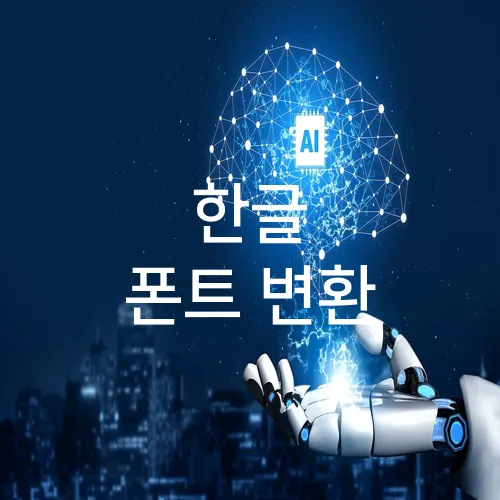
1. 한글 폰트 변환: 사용하기 쉬운 도구 및 애플리케이션
한글 폰트 변환을 위한 쉽고 유용한 도구
한글 폰트 변환은 많은 사람들이 다양한 목적을 위해 필요로 합니다. 이렇게 다양한 목적을 이루기 위해서는 사용하기 쉬운 도구와 애플리케이션이 중요합니다. 먼저, 대표적인 도구인 네이버 클라우드의 ‘네이버 폰트’는 100여 가지 이상의 다양한 폰트를 제공하여 사용자들이 손쉽게 자신만의 스타일을 완성할 수 있게 도와줍니다.
다음으로 추천할 만한 도구는 어도비의 ‘어도비 폰트’입니다. 이 도구는 웹 기반의 그래픽 작업 시 자동으로 폰트를 동기화하여 빠르고 효율적인 작업이 가능하도록 합니다. 특히, 어도비 스위트를 사용하는 디자이너들에게 최적화된 옵션입니다.
누구나 사용 가능한 무료 애플리케이션
무료로 제공되는 ‘구글 폰트’는 웹에서 바로 사용 가능한 오픈 소스 폰트 라이브러리로, 누구에게나 추천할 만한 서비스입니다. 다양한 글꼴을 웹 페이지에 적용하기 용이하며, 한글뿐만 아니라 다국어 폰트도 쉽게 변환할 수 있습니다.
또한, ‘다폰트 (Dafont)’는 사용하기 쉬운 사용자 인터페이스로 초보자도 손쉽게 필요한 폰트를 다운로드하여 사용할 수 있습니다. 특히, 상업적 이용 여부를 명확히 표시해줘 디자이너들이 안전하게 사용할 수 있습니다.
온라인 기반의 간편한 폰트 변환 기능
‘폰트 스퀘어’는 온라인에서 간단하게 폰트를 변경할 수 있는 서비스로, 별도의 프로그램 설치 없이 다양한 폰트를 테스트해볼 수 있습니다. 또한, 미리보기를 통해 지정된 텍스트가 실제로 어떻게 보일지 확인할 수 있습니다.
마지막으로, ‘윈도우 10’ 자체 기능으로도 기본 내장된 여러 한글 폰트를 쉽게 변경할 수 있으며 시스템 설정을 통해 간단히 적용이 가능합니다. 특히, 오피스 프로그램과의 호환성이 뛰어납니다.
이처럼 다양한 도구와 애플리케이션을 활용하면 한글 폰트 변환을 보다 쉽게 수행할 수 있습니다. 여러 옵션을 비교하고 자신의 니즈에 맞는 도구를 선택해보세요.
2. 웹사이트에서 한글 폰트 변환의 최신 트렌드
최신 웹사이트 트렌드
요즘 웹디자인에서 한글 폰트 변환이 어떻게 적용되고 있는지에 대한 트렌드를 살펴보겠습니다. 웹사이트는 단순히 정보를 전달하는 것을 넘어 감성을 표현하는 미디어로 자리잡고 있습니다. 특히 한글 폰트의 경우 시각적인 효과를 더욱 돋보이게 할 수 있어 많은 디자이너들이 주목하고 있습니다.
• 네이버와 카카오 같은 대형 포털 사이트는 최신 폰트 기술을 적극적으로 활용해 사용자의 가독성을 높이고 있습니다. 반응형 웹디자인과 같은 방식으로 다양한 기기에서 최적의 폰트 크기와 형태를 유지합니다.
• 웹폰트 서비스인 산돌클라우드와 같은 플랫폼은 사용자가 쉽게 웹사이트에 한글 폰트를 적용할 수 있는 환경을 제공하고 있습니다. 다양한 폰트 라이브러리를 통해 브랜딩에 맞는 폰트를 빠르게 적용할 수 있습니다.
디지털 환경에서의 한글 폰트 활용
디지털 디자인에서 한글 폰트 변환은 로딩 속도 최적화와 밀접하게 관련되어 있습니다. 최적화된 폰트는 웹페이지 로딩 시간을 줄이며, 이는 검색 엔진에서도 긍정적인 영향을 미칩니다.
• 구글 웹폰트와 이와 비슷한 서비스는 용량을 최소화한 폰트를 제공하여 페이지 로딩 속도를 개선합니다.
• 또한, 사용자 경험을 고려해 적절한 레이아웃과 폰트 크기를 적용함으로써 접근성을 높이는 것이 중요합니다.
변화하는 웹디자인 트렌드에 발맞춰 한글 폰트 변환 기술과 활용법을 이해하고 적용한다면, 더욱 매력적이고 효과적인 웹사이트를 구축할 수 있습니다. 이러한 트렌드는 사용자 만족도를 증대시키고 브랜드 이미지를 강화하는 데 큰 도움이 됩니다.
3. 한글 폰트 변환 시 주의해야 할 폰트 호환성 문제
한글 폰트 변환의 중요성
한글 폰트 변환을 할 때 가장 중요한 것은 호환성입니다. 이는 서로 다른 소프트웨어나 디지털 플랫폼 간에 문서를 공유할 때 발생할 수 있는 문제를 피하기 위해 필수적입니다. 최근 Adobe의 ‘한글본’이나 네이버의 ‘나눔글꼴’ 같은 무료 폰트는 높은 인기를 끌고 있지만, 여전히 폰트마다 호환성 이슈가 존재할 수 있습니다.
– 사용 중인 소프트웨어의 지원 폰트 리스트를 항상 확인하세요.
– 다양한 플랫폼에서 테스트하여 글꼴이 제대로 적용되었는지 확인하세요.
호환성 문제의 원인과 해결책
한글 폰트 변환 시 문제는 주로 문자 코드와 관련이 깊습니다. 특히 구형 소프트웨어와 신형 폰트를 사용할 때 이러한 문제가 자주 발생합니다. MS 워드와 같이 많은 사람들이 사용하는 프로그램에서도, 오래된 버전에서는 새롭게 출시된 한글 폰트가 깨질 수 있습니다.
– 최신 소프트웨어로 업그레이드하여 문제를 방지하세요.
– Google Docs 같은 클라우드 기반 서비스는 자동 변환 기능을 제공하여 호환성을 높입니다.
안정적인 폰트 변환을 위한 팁
변환 전, 항상 백업을 만들고 테스트 문서를 준비하는 것이 좋습니다. InDesign 같은 그래픽 소프트웨어는 복잡한 레이아웃에서도 폰트 호환성을 유지하는 데 유용합니다.
– Adobe Fonts를 이용하면 다양한 플러그인과 호환 가능합니다.
다양한 플랫폼에서의 테스트
모바일과 웹에서도, 한글 폰트는 각기 다른 해상도와 환경에서 다르게 보일 수 있습니다. 따라서 실제 사용 환경에서 폰트가 어떻게 보이는지 테스트하세요.
– iOS와 Android 모두에서 테스트하여 모바일 호환성을 높이세요.
– 웹사이트 구축 시, 다양한 브라우저에서의 시각적 차이를 점검하세요.
이러한 방법들을 통해 적절한 한글 폰트 변환을 거쳐, 프로젝트의 완성도를 높여보세요.
4. 창의적인 디자인을 위한 한글 폰트 커스터마이징 팁
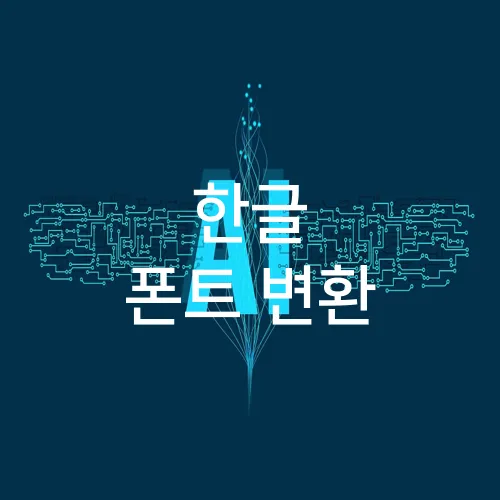
폰트 선택의 기본 전략
창의적인 디자인을 위해서는 한글 폰트 변환의 기초부터 이해하는 것이 중요합니다. 먼저, 프로젝트의 성격과 목적에 맞는 폰트를 선택하는 것이 핵심입니다. 예를 들어, 공공 기관의 발표 자료는 나눔고딕이나 서울남산체와 같은 공식성과 가독성을 강조하는 폰트를 사용할 수 있습니다.
폰트는 사용 목적에 따라 크게 디스플레이 폰트와 본문용 폰트로 나누어질 수 있습니다. 디스플레이용은 큰 타이포그래피를 만들 때 효과적이며, 제목이나 강조할 메시지에 적합합니다. 본문용 폰트는 가독성이 높아 장시간 읽기에 편안해야 합니다.
효과적인 폰트 커스터마이징 팁
폰트를 선택한 후에는 다양한 툴을 활용하여 개인 맞춤형 스타일을 적용할 수 있습니다. Adobe Illustrator나 Affinity Designer와 같은 도구를 활용하면, 기본 폰트에 그림자나 윤곽선과 같은 이펙트를 추가할 수 있어 독특한 디자인을 연출할 수 있습니다.
여러 폰트를 적절히 결합하는 것도 한글 폰트 변환의 중요한 기술입니다. 서로 다른 가중치의 폰트를 조합하면 원하는 강조 효과를 줄 수 있습니다. 예를 들어, 헤드라인에는 굵은 폰트를, 본문에는 얇은 폰트를 사용하는 것이 좋습니다.
폰트 사용 시 주의할 점
폴더 시스템이나 클라우드 저장소를 이용하여 사용 중인 모든 폰트를 정리하는 것이 중요합니다. 그래야 필요할 때 효과적으로 검색하고 활용할 수 있습니다.
또한, 상업 프로젝트에 무료 폰트를 사용하려면 라이선스 조건을 반드시 확인해야 합니다. 많은 무료 폰트는 개인 용도로는 무료지만, 상업적 사용에는 제한이 있을 수 있습니다. 이는 디자인의 법적 문제를 예방하는 데 필수적입니다.
이와 같은 방법들을 활용하면 효과적으로 창의적인 디자인을 돋보일 수 있습니다.
5. 한글 타이포그래피: 효율적인 변환을 위한 기본 원칙
한글 폰트 변환의 중요성
한글 문서를 디자인할 때, 폰트 변환은 필수적입니다. 폰트는 텍스트의 가독성을 높이고, 정보의 전달력을 강화하는데 큰 역할을 합니다. 특히 한글 폰트 변환은 디지털 환경에서 더욱 중요해졌습니다.
– 주요 문서 작성에 널리 사용되는 나눔바른고딕, 본고딕 같은 폰트는 깔끔한 디자인을 갖추고 있어, 공공기관 및 기업에서도 많이 활용하고 있습니다.
– 이러한 폰트를 사용할 경우, 라이선스를 반드시 확인하여야 하며, 필요시 네이버의 나눔폰트 공식 사이트에서 무료로 다운로드 받을 수 있습니다.
효율적인 폰트 변환을 위한 도구
효율적인 한글 폰트 변환을 위해서는 적절한 도구 선택이 중요합니다.
– 어도비 인디자인은 다양한 폰트 변환 기능을 제공하여 고급 디자인 작업에 적합합니다.
– 마이크로소프트 워드는 폰트 호환성이 우수하여 일반 문서 작업 시 편리합니다.
이 밖에도, 크롬 확장 프로그램인 ‘Font Changer’를 사용하면 상황에 맞춰 손쉽게 웹 브라우저에서 폰트를 변환할 수 있어 유용합니다.
기본 원칙: 가독성과 목적성
한글 타이포그래피를 통해 변환할 때, 가장 중요하게 고려해야 할 요소는 가독성입니다.
– 지나치게 화려한 폰트는 디자인을 방해하고 독자의 집중력을 떨어뜨릴 수 있습니다.
– 읽기 쉬운 고딕체나 명조체를 사용하여 정보를 명확하게 전달하세요.
또한, 텍스트의 목적성을 고려해야 합니다. 예를 들어, 공식 문서에는 신뢰감을 주는 폰트를, 광고에는 시선을 끄는 폰트를 활용하면 효과적입니다.
– Adobe Fonts: 프리미엄 서비스로 고품질 폰트를 제공합니다.
– Google Fonts: 무료로 접근 가능하며 개인 및 상업적 용도로 다양하게 활용됩니다.
웹 환경에서의 폰트 적용
디지털 콘텐츠는 다양한 디바이스에서 읽히기 때문에 웹 호환성이 중요합니다. CSS를 활용한 웹폰트 적용은 페이지 로딩 속도에 영향을 미칠 수 있으므로 최적화가 필요합니다. 구글에서 제공하는 웹폰트 최적화 팁을 참고하면 성능 개선에 도움이 됩니다.
폰트 관리는 쉽고 편리하게
많은 폰트를 관리하는 것은 번거롭게 느껴질 수 있습니다. 네이버 클라우드나 드롭박스와 같은 클라우드 스토리지 서비스를 활용하면 중앙에서 손쉽게 폰트를 관리할 수 있습니다. 이를 통해 작업 간소화와 데이터 백업 문제를 동시에 해결할 수 있습니다.
– 네이버 클라우드: 손쉬운 접근성과 안정적 관리를 제공합니다.
– 드롭박스: 다중 디바이스에서의 손쉬운 동기화가 가능합니다.
적절한 폰트 선택과 효율적인 관리는 사용자 경험을 크게 향상시킵니다. 다양한 도구를 활용하고 꾸준히 관리하면 디자인 프로젝트의 완성도를 높일 수 있습니다.